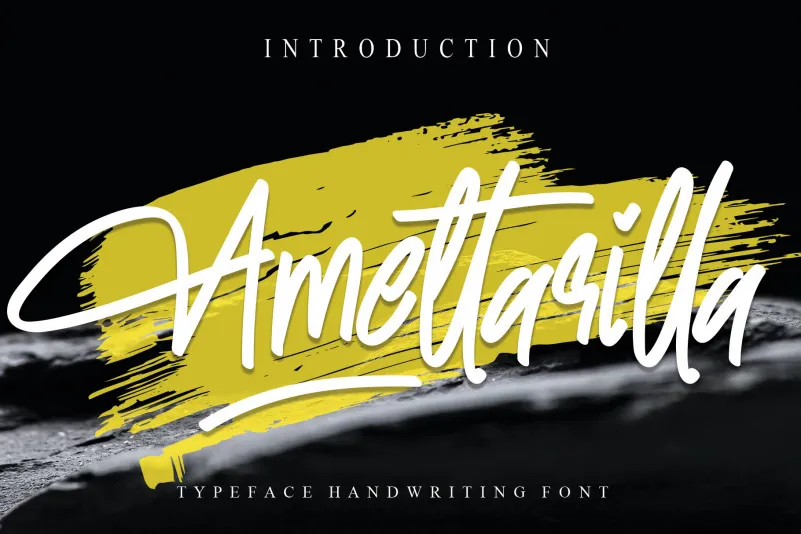
Amettarilla Handwritten Font – Download Grátis
Amettarilla Handwritten Font é uma elegante escolha para qualquer projeto que deseja incorporar um toque delicado e pessoal aos seus designs digitais. Esta fonte escrita à mão oferece linhas suaves, traços variados e uma personalidade única que pode complementar desde cartazes de propaganda até anúncios de moda ou letras de música. As características fluidas da Amettarilla transmitem uma sensação de conforto e familiaridade, tornando-a perfeita para aplicativos em quaisquer contextos que requerem um contraponto suave à estética mais complexa dos designs digitais. Escolha esta fonte para adicionar a sua próxima peça gráfica um toque de originalidade e emoção pessoal, que certamente não será esquecido por seus usuários finais.